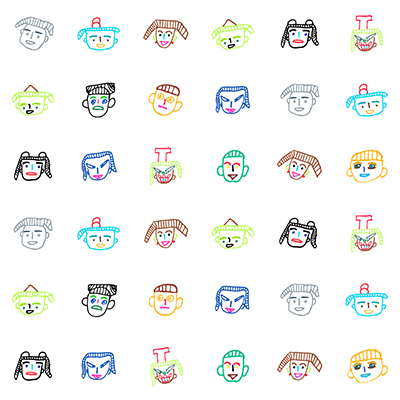
シブヤフェイス
渋谷には色んな人がいる。それだけ色んな顔がある。十人十色なみんなの顔をよく見てみると、それぞれに違った魅力が見つかります。みんなが自分自身、互いの良さに気づいてほしい、という思いを込めました。(吉岡 風美)
普段から身近な人をたくさん描いてくれています。面白い形で書き進めてくれ、毎回楽しそうに説明してくれます。描き出す人が一人一人個性があり面白いデザインになっています。(ワークささはた)